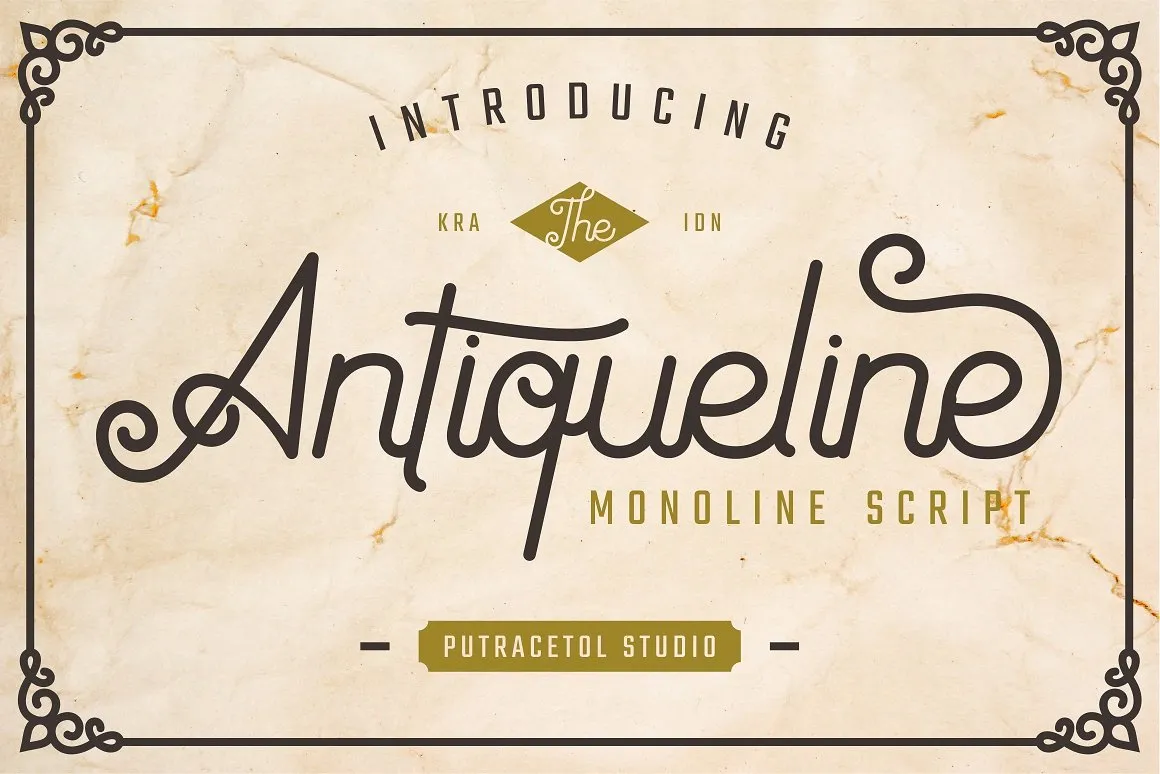
Antiqueline Script Font – Download Grátis
Olá todos! Para aqueles apaixonados por fontes, hoje temos a honra de apresentar a “Antiqueline Monoline Typeface”, uma nova fonte monoliné que promete adicionar um toque único ao seu trabalho gráfico e digital. A C00zona nos presenteia com esta novidade que traz características únicas para qualquer projeto. A Antiqueline possui uma riqueza em estilo tanto clássico quanto retro, combinando sofisticação com simplicidade de forma. Seja para criar um logo memorável ou uma identidade visual impecável, uma carta de boas-vindas especializada ou até mesmo cartões personalizados. Este tipo de fonte é perfeito para aquelas criações que exalam um ar vintage, proporcionando aos seus projetos um toque único e autêntico. O destaque da Antiqueline está em seu design elegante e minimalista, com ligaduras e alternativas de letras adicionadas ao conjunto. Esta fonte é altamente versátil e está equipada para atender a múltiplas línguas, tornando-a um recurso valioso para designers de todos os níveis e gostos. Descubra o encanto da Antiqueline Monoline Typeface para se beneficiar do seu estilo único e sofisticado. Com certeza será uma fonte que vai fazer a diferença em seus projetos digitais!